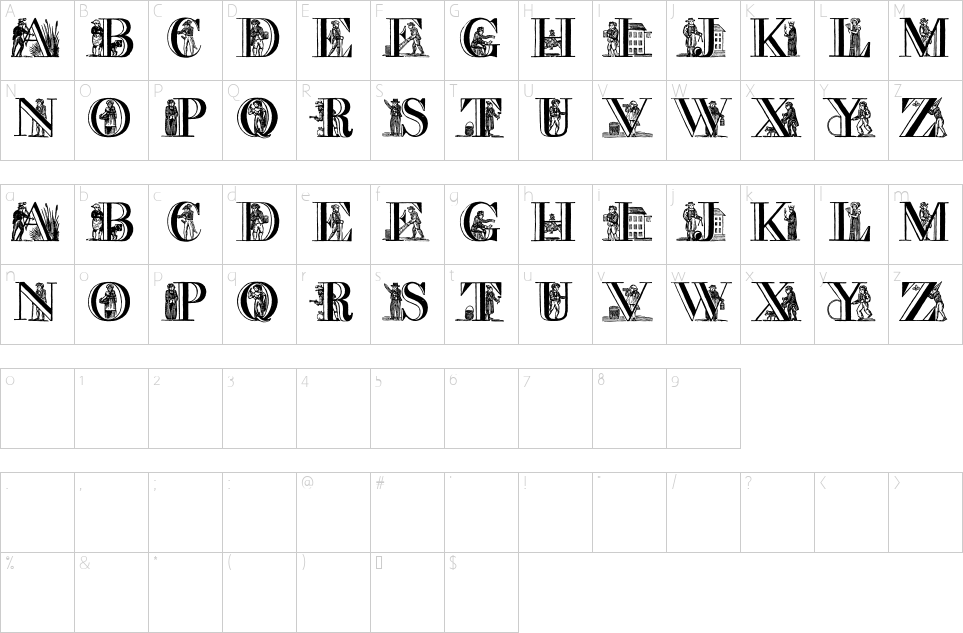
A fonte ‘Picture Alphabet Font’ é uma opção ideal para quem procura um estilo simples e alegre para adicionar um toque personalizado a textos e ilustrações. Desenhada pelo designer Dieter Steffmann, esta fonte abrange a totalidade do alfabeto e é uma ótima escolha para aqueles que buscam uma fonte versátil para trabalhos de design gráfico, desde criações digitais até diagramação impressa. Conhecida por sua simplicidade e alegria, a ‘Picture Alphabet Font’ pode ser facilmente instalada tanto em sistemas Windows quanto Mac. Com uma facilidade de uso e um design agradável, é surpreendente ver que já foi baixada mais de 20.000 vezes, demonstrando a sua popularidade e qualidade. Seja para criar cartazes, adesivos, desenhos digitais ou qualquer outro trabalho de design que exija um toque alegre, esta fonte é uma excelente opção.